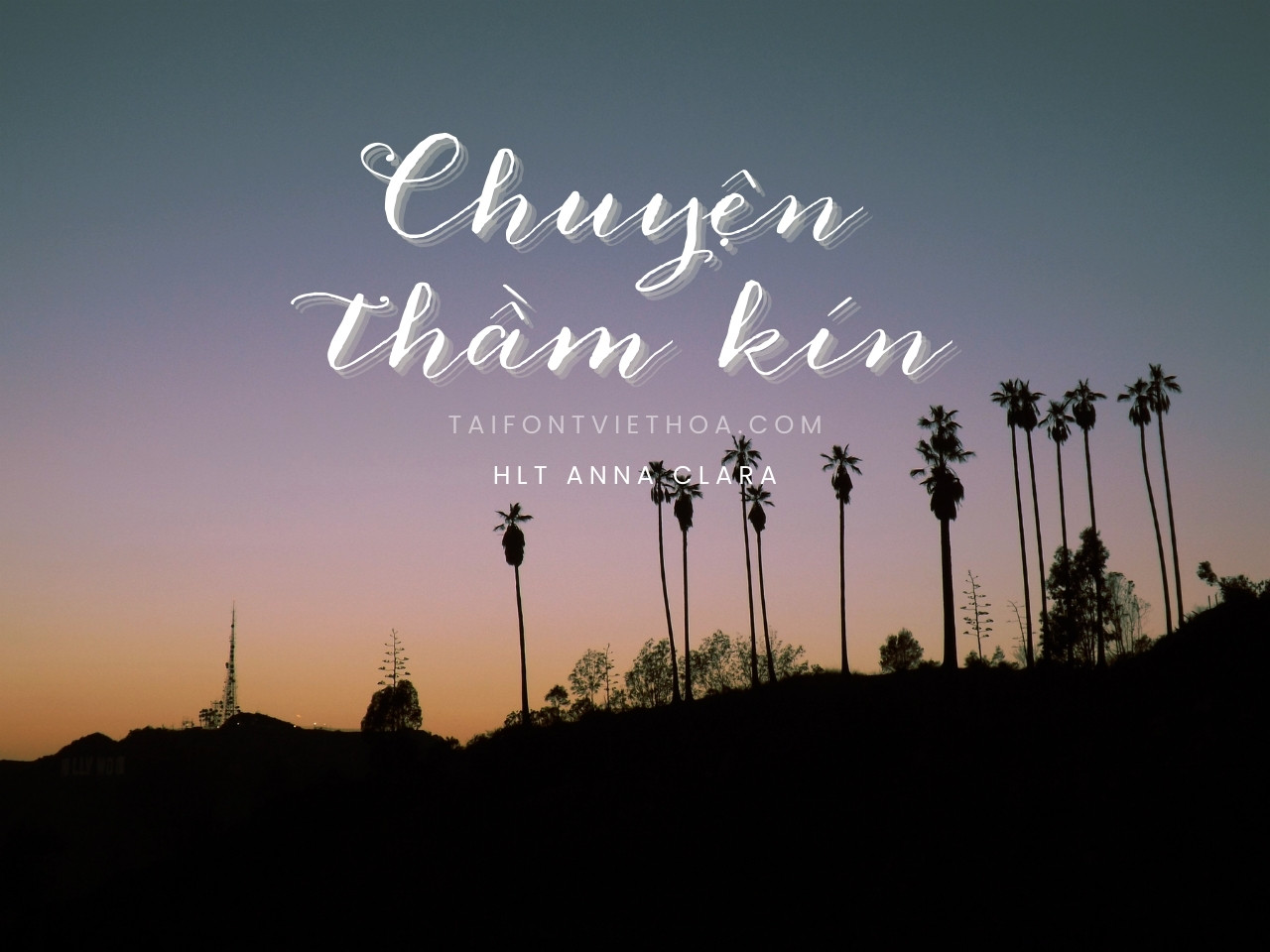
Giới thiệu về font HLT Anna Clara – Nét viết tay hiện đại mang cảm xúc lãng mạn
HLT Anna Clara là phiên bản Việt hóa của font “Anna Clara Script” – một kiểu chữ handwritten mang phong cách nhẹ nhàng, nữ tính, được phát triển bởi Maulana Creative – một nhà thiết kế đến từ Indonesia nổi tiếng với các bộ font viết tay nghệ thuật. Font gốc được phát hành qua nhiều nền tảng chia sẻ font quốc tế, hỗ trợ hơn 60 ngôn ngữ sử dụng bảng chữ cái Latinh, tạo điều kiện ứng dụng linh hoạt trong nhiều dự án toàn cầu.
Phiên bản Việt hóa do HLT Fonts thực hiện với sự chăm chút kỹ lưỡng, đảm bảo hỗ trợ đầy đủ bảng ký tự tiếng Việt có dấu và các glyphs đặc trưng. Quá trình Việt hóa không chỉ dừng lại ở chuyển đổi ngôn ngữ, mà còn điều chỉnh tỉ lệ nét chữ, kerning và độ cân bằng nhằm tạo ra trải nghiệm thị giác tối ưu cho người dùng Việt. Font này đã được taifontviethoa.com lựa chọn, kiểm duyệt kỹ lưỡng và chia sẻ nhằm phục vụ cộng đồng sáng tạo trong những dự án mang tính nghệ thuật và cá nhân hóa.
Phong cách thiết kế uyển chuyển và ứng dụng thực tiễn của HLT Anna Clara
HLT Anna Clara có cấu trúc chữ mềm mại, đường nét thanh thoát như những nét bút tay uyển chuyển. Các ký tự nối liền với ligatures tự nhiên, mang lại cảm giác chân thực và duyên dáng. Nhờ yếu tố này, font tạo ra hiệu ứng như chữ viết tay thực sự, giúp tăng tính cá nhân và sự gần gũi cho thiết kế.
Font đặc biệt phù hợp với các dự án như thiệp cưới, thiết kế đồ họa mang hơi thở lãng mạn, quote typography, poster, bao bì mỹ phẩm và thương hiệu thời trang nữ. Ngoài ra, HLT Anna Clara cũng rất được ưa chuộng trong các thiết kế truyền thông mạng xã hội, blog cá nhân và những nội dung mang đậm dấu ấn cảm xúc.